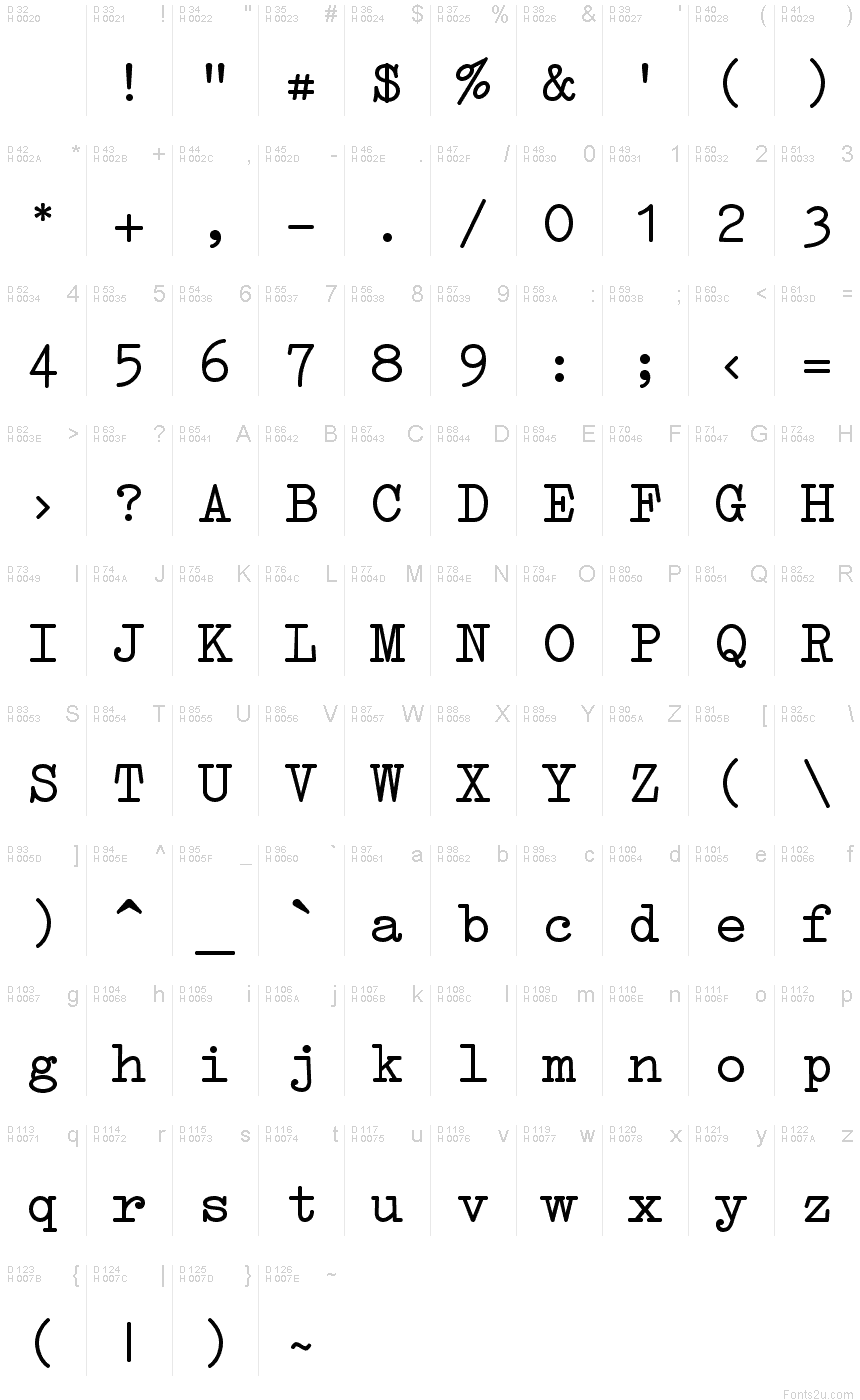
Erica Type Italic od Petera Wiegela je bezplatné doskové písmo (slab serif) v štýle písacieho stroja so staromódnym tlačeným vzhľadom. Široké serify, pevné ťahy a jemne zmäkčené okraje dodávajú písmenám nerovný vzhľad atramentu vtlačeného do papiera.
Vydavateľstvá sa hodia k jeho mechanickej štruktúre, najmä pre nadpisy v časopisoch, knižné obálky a programy literárnych podujatí. Obalom môže dodať aj praktický šarm štítku napísaného na stroji. Písmo pôsobí archívne. Vďaka tejto vlastnosti sa obzvlášť hodí pre historickú prózu, detektívne príbehy a projekty postavené na korešpondencii alebo kancelárskych záznamoch.